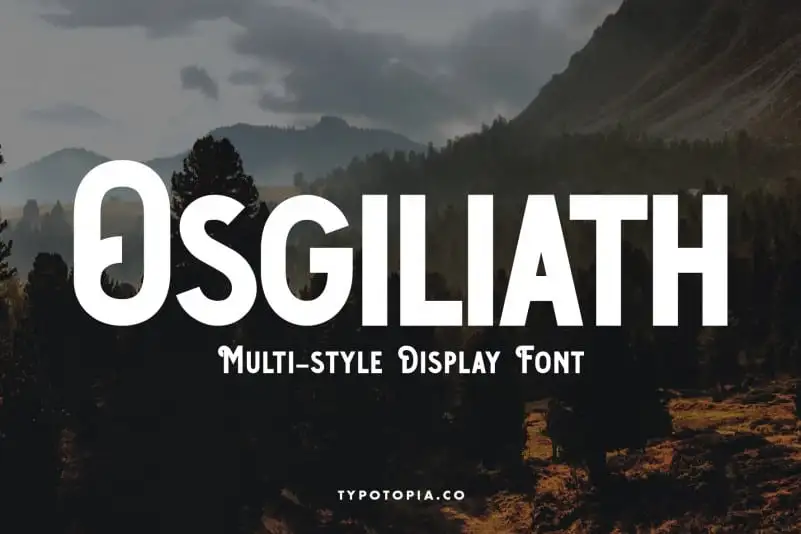
Osgiliath Multistyle Display Font – Download Grátis
Osgiliath Multistyle Display Font é uma elegante fonte para destaque que carrega consigo a essência única e intrigante do design tipográfico. Com sua rica variedade de estilos, essa fonte se torna perfeita para destacar textos em cartões de convidado, websites, ou qualquer outra aplicação onde um toque especial é desejável. Desenvolvida pelo designer experiente da typotopia, esta fonte oferece tanto estilo quanto funcionalidade, proporcionando uma experiência visual memorável e agradável ao usuário. Composta por múltiplos estilos, você pode adaptá-la para criar texturas de um texto simples até um texto exuberante com acabamentos elegantes. Essa é a escolha perfeita para quem busca um recurso gráfico que seja tanto funcional quanto atraente.